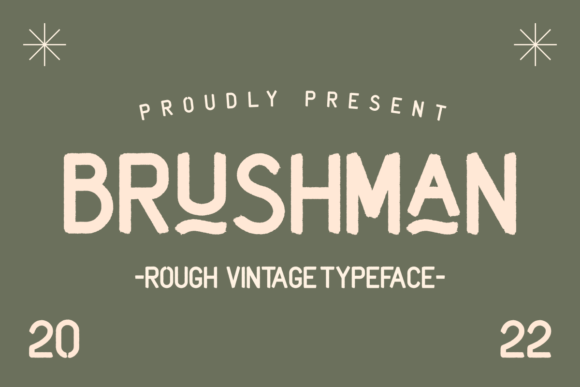
Brushman, fuente de pincel dibujada a mano para carteles y gráficos creativos
Brushman 2 es una fuente de visualización de estilo pincel que ofrece una estética robusta y artesanal, perfecta para gráficos, señalización, pósteres y artículos de merchandising de inspiración vintage. Sus trazos texturizados y su carácter orgánico otorgan a los diseños un aspecto audaz y expresivo, ideal para crear titulares, logotipos y branding llamativos y con personalidad. Como recurso tipográfico digital, se integra a la perfección en flujos de trabajo de diseño, impresión bajo demanda y máquinas de manualidades.
- Logotipos y marcas con un aspecto vintage/hecho a mano
- Carteles, folletos, pancartas, señalización: perfectos para titulares llamativos y textos de exhibición.
- Artículos de merchandising y POD: ropa, tazas, bolsas de tela, pegatinas, impresiones
- Redes sociales y gráficos digitales: banners, gráficos de citas, arte digital con carácter
- Proyectos de corte y manualidades: calcomanías de vinilo, letreros de papel, maquetas, etiquetas de embalaje
- Letras texturizadas hechas a mano con estilo de pincel para una estética distintiva y expresiva
- Alta visibilidad e impacto: ideal para textos de visualización, encabezados y diseños llamativos.
- Flexible en proyectos impresos, digitales, de merchandising y de manualidades.
| Característica | El hombre del cepillo 2 | Fuente genérica limpia sans-serif A | Fuente de visualización genérica B (simple) |
| Estilo / Vibra | Pincel texturizado / hecho a mano / exhibición vintage | Sans-serif limpio y neutro | Pantalla simple sans-serif |
| Mejor para | Logotipos, carteles, merchandising, señalización, diseños vintage/hechos a mano | Cuerpo de texto, diseños limpios, marca moderna | Encabezados o texto de visualización que necesitan simplicidad |